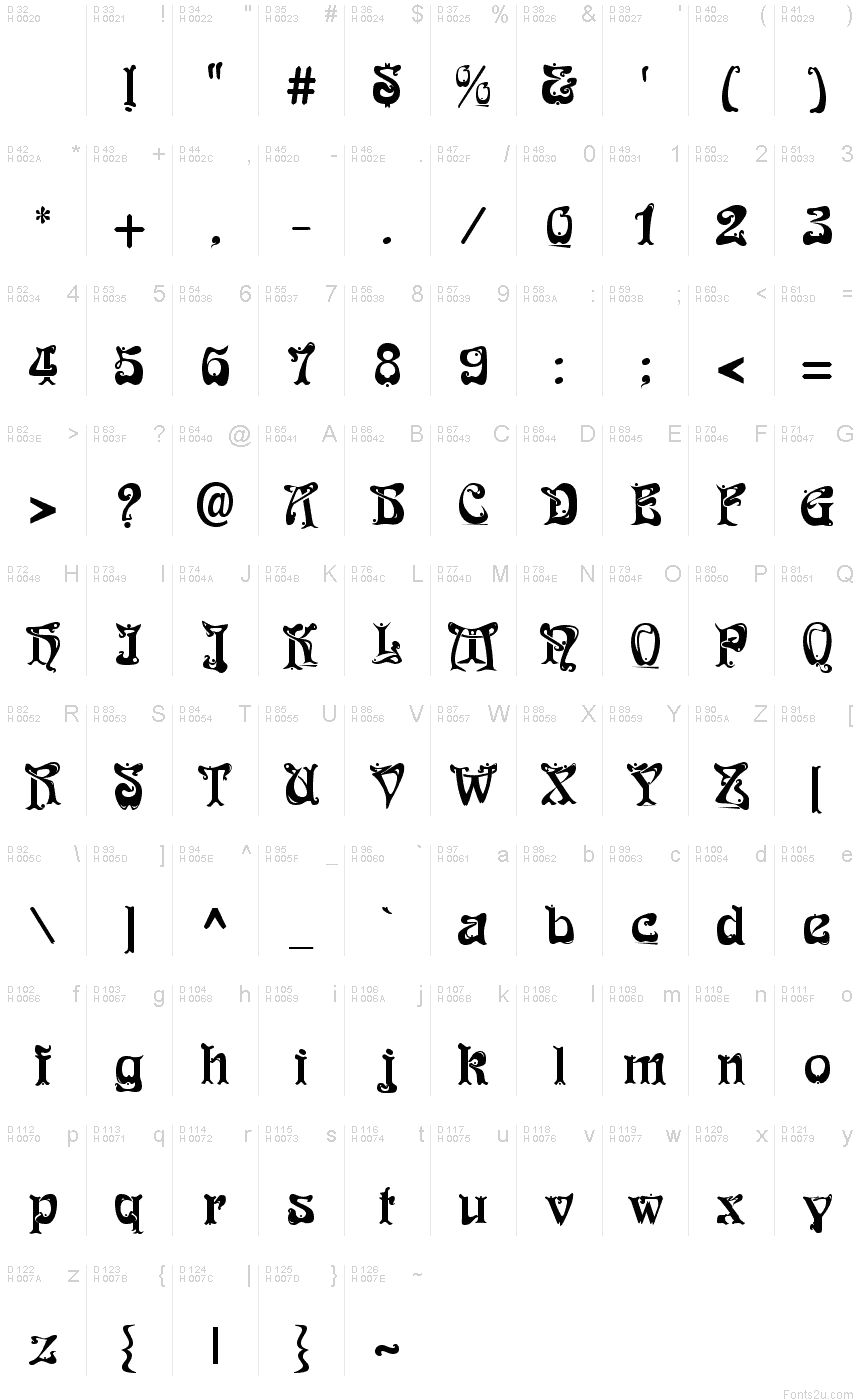
Funk Regular
Funk od Buddha Graphix to darmowy, dekoracyjny krój pisma w stylu retro, który zamienia każde słowo w wirującą grafikę plakatową. Grube, przypominające tusz krzywe przechodzą w ostre, inspirowane gotykiem krawędzie, a zabawne wycięcia i niemal figuratywne kształty nadają literom psychodeliczny, dynamiczny charakter. Całość wygląda jak zderzenie klasycznych plakatów rockowych z estetyką undergroundowych zinów, z gładką, błyszczącą teksturą, która na stronie sprawia wrażenie niemal płynnej.
Dzięki Funk Twoje nagłówki staną się natychmiast wyraziste, oryginalne i niezapomniane – to świetny wybór na plakaty koncertowe, okładki albumów, branding festiwalowy, klubowe ulotki, logotypy streetwearowe i psychodeliczne grafiki. Ten darmowy font najlepiej sprawdza się w dużym rozmiarze i pogrubieniu, gdzie jego nietuzinkowe detale mogą w pełni wybrzmieć; w tekście głównym zestaw go z prostym, neutralnym krojem bezszeryfowym, aby zachować czytelność i równowagę.